Font chữ thời trang việt hóa là font có phong cách elegant, high-contrast với đặc điểm mảnh, thanh lịch được sử dụng rộng rãi trong thiết kế bao bì thời trang cao cấp, túi giấy boutique và in ấn cho thương hiệu luxury. Font thời trang việt hóa với nét chữ refined, sophisticated tạo cảm giác sang trọng, chic.
Ở bài viết này, In Viva giới thiệu font chữ thời trang với hơn 12 mẫu miễn phí có phong cách Vogue, Harper’s Bazaar phù hợp cho thiết kế bao bì và in ấn thời trang.
Font thời trang là gì?
Font thời trang (fashion font) là font được các tạp chí thời trang, thương hiệu luxury sử dụng – đặc trưng bởi Modern serif với tương phản cực cao hoặc sans-serif elegant minimalist.
Đặc điểm font thời trang:
- High contrast – tương phản cao: Nét dọc cực đậm, nét ngang cực mỏng (hairline) – signature của Modern serif như Didot, Bodoni.
- Elegant, refined: Nét chữ thanh lịch, tinh tế, không một chi tiết thừa – epitome của sophistication.
- Thin, delicate: Nhiều font fashion ở weight Thin, Light – tạo cảm giác nhẹ nhàng, ethereal.
- Vertical stress: Chữ tròn có trục thẳng đứng (không nghiêng) – tạo cảm giác formal, regal.
Font iconic của ngành thời trang:
- Vogue Magazine: Didot – font Modern serif Pháp (1784), tương phản cực cao. Vogue dùng Didot từ nhiều thập kỷ, tạo identity mạnh mẽ.
- Harper’s Bazaar: Didot variants và Bodoni – cùng họ Modern serif.
- Giorgio Armani: Didot – nhất quán với luxury positioning.
- Burberry: Custom serif elegant – inspired by Bodoni.
- Massimo Dutti: Didot-style serif.
Playfair Display |
Modern/Transitional serif elegant | Logo thời trang, túi giấy boutique |
Libre Bodoni |
Modern serif high contrast | Bao bì luxury, magazine fashion |
Cormorant |
Display serif elegant, 10 weights | Catalogue haute couture, lookbook |
Cinzel |
Roman capitals elegant | Logo luxury brand, header formal |
Bodoni Moda |
Modern serif, 18 weights | Editorial fashion, catalogue premium |
Yeseva One |
Display serif bold elegant | Poster fashion show, standee event |
Marcellus |
Classical serif refined | Logo heritage fashion, luxury classic |
Amiri |
Arabic-inspired elegant serif | Middle East luxury brand, exotic feel |
Montserrat Thin |
Geometric sans ultra thin | Logo minimalist fashion, modern chic |
Raleway Thin |
Elegant sans thin | Catalogue contemporary fashion |
Lưu ý: Modern serif (Didot-style) với nét hairline rất mỏng có thể bị mất khi in kích thước nhỏ hoặc trên giấy thấm. Nên test in thử và tránh dùng kích thước dưới 10pt cho text, 24pt+ cho display.
Ứng dụng font thời trang trong bao bì luxury
Font chữ thời trang với phong cách elegant được ưa chuộng:
- Fashion industry standard: Modern serif (Didot, Bodoni style) là “uniform” của high fashion – Vogue, Harper’s Bazaar, Armani đều dùng, tạo instant luxury association.
- Feminine, sophisticated: Nét mảnh elegant đặc biệt phù hợp women’s fashion, lingerie, jewelry – nhấn mạnh femininity, refinement.
- Editorial quality: Font thời trang tạo cảm giác magazine editorial, photoshoot high-end – elevate product perception.
- Minimalist luxury: Thin sans (Montserrat Thin, Raleway Thin) cho contemporary fashion minimalist – Céline, Jil Sander aesthetic.
Font thời trang xuất hiện trong nhiều sản phẩm in ấn:
- Bao bì thời trang cao cấp: hộp giày designer, hộp quần áo luxury, shopping bag high-end.
- Túi giấy boutique: túi couche, kraft premium cho boutique, flagship store.
- Catalogue thời trang: lookbook collection, fashion show catalog, editorial spread.
- Nhãn quần áo: woven label, care label với font refined.
- Thiệp mời fashion event: fashion show invitation, VIP sale, trunk show.
- Poster quảng cáo: billboard campaign, magazine ad, in-store poster.
- Brochure luxury: brand book, heritage story, craftsmanship booklet.
- Bao bì jewelry: jewelry box, watch box với typography elegant.
- Menu fashion cafe: cafe inside boutique, fashion district bistro.
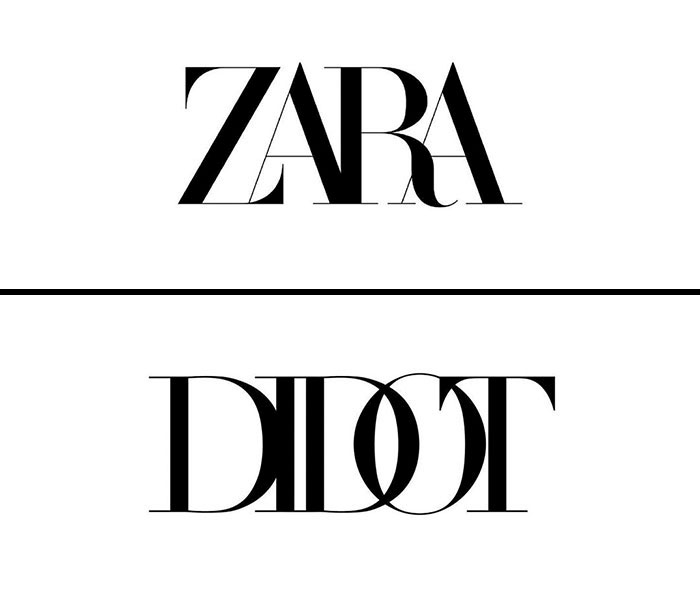
2. Khi nào dùng serif, khi nào dùng sans cho thời trang?
Dùng Modern serif (Didot-style) cho: classic luxury, women’s fashion, editorial, formal. Dùng thin sans (Montserrat Thin) cho: contemporary minimalist, menswear modern, streetwear upscale, Scandinavian aesthetic.
3. Font thời trang có dễ in không?
Modern serif với nét hairline khó in kích thước nhỏ – có thể bị mất nét. Cần: (1) kích thước tối thiểu 10pt cho text, 24pt+ cho display, (2) giấy không thấm (couche, ivory), (3) in offset chất lượng cao.